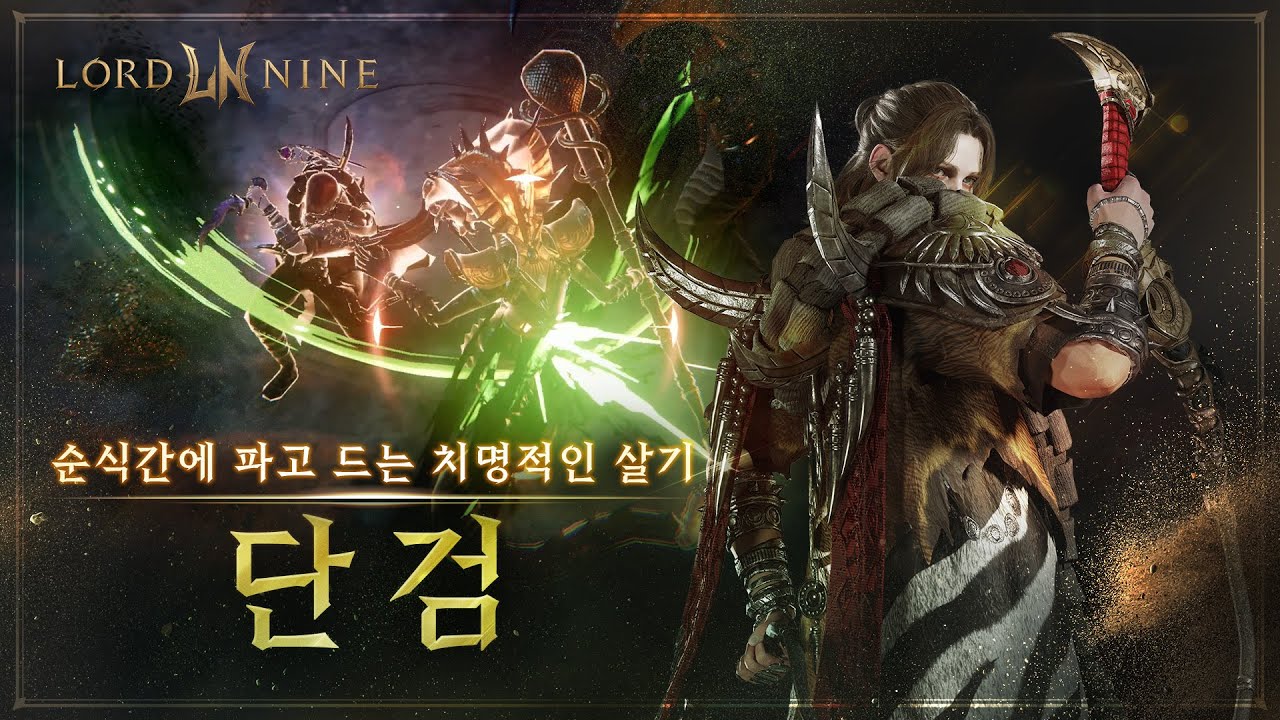
NX3GAMES 로드나인 [TheOneLord]
NX3GAMES 에서 개발한 게임 '로드나인'의 전용서체 [TheOneLord]는 비석에 새긴 비범한 목소리, 횃불의 맹렬한 불꽃을 모티프로 제작한 서체이다. 치열한 전쟁을 직선과 사선, 획의 패임 등으로 시각화하여 자소와 세리프의 형태, 글줄에서 긴장감과 속도감이 느껴지는 것이 특징이다.